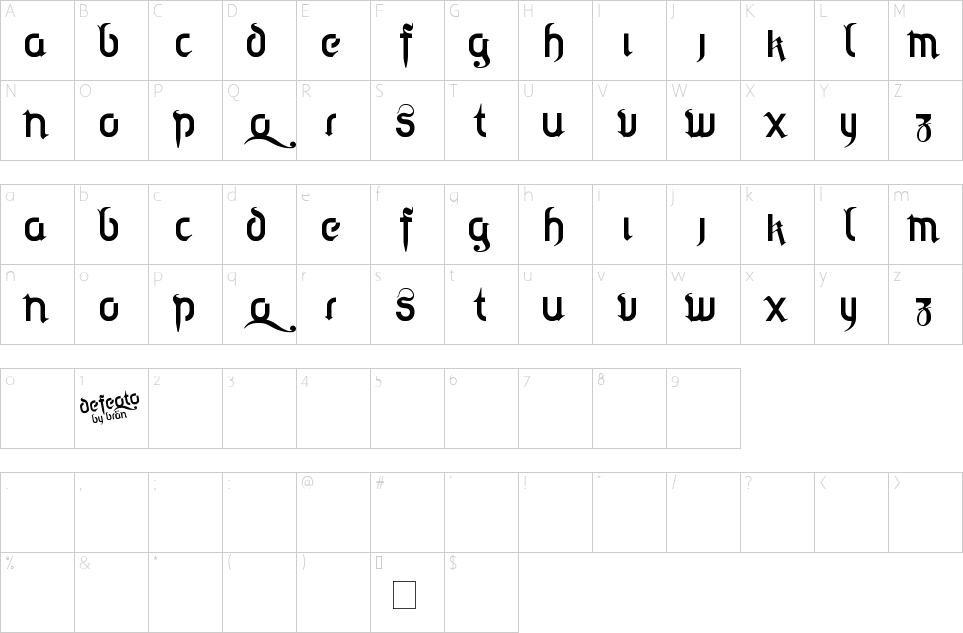
A Defeqto Font é uma elegante escolha para quem busca estilo e simplicidade na hora de personalizar textos em suas criações digitais. Desenhada por Bran, essa fonte oferece um acabamento sofisticado que combina bem com diversos estilos gráficos. A Defeqto é perfeita para adicionar uma camada extra de interesse a qualquer projeto digital. Com seus 4,580 downloads ao longo da sua história, ela já conquistou o favor do público em busca de fontes modernas e versáteis. Se você está procurando por uma fonte que combine elegância com facilidade de uso, Defeqto é um excelente escolha para suas necessidades. Descubra seu potencial na hora de criar e faça da sua próxima criação algo único e atraente com essa fonte única.